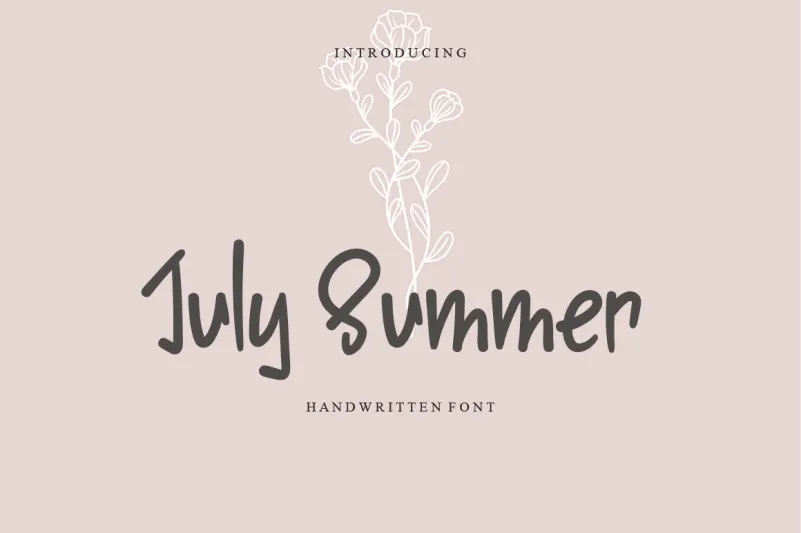
July Summer Font – Fonte Grátis
July Summer Font
Esta é uma fonte feita à mão com características únicas e divertidas, perfeita para quem busca dar um toque especial aos seus projetos digitais. Ela combina a elegância do estilo manual com a facilidade de uso de uma fonte escrita à mão livremente. Se você está buscando uma fonte ideal para criar postagens carregadas de personalidade no Instagram, ou mesmo para criar scripts meticulosamente cuidados em um projeto DIY, esse é o tipo perfeito de font que você procura. Esta font faz com que qualquer ideia criativa brilhe ainda mais, tornando-a uma verdadeira obra-prima visual. Ideal tanto para designer profissional quanto para os entusiastas de design iniciantes, ela oferece flexibilidade para transformar suas criações digitais em verdadeiras obras de arte.